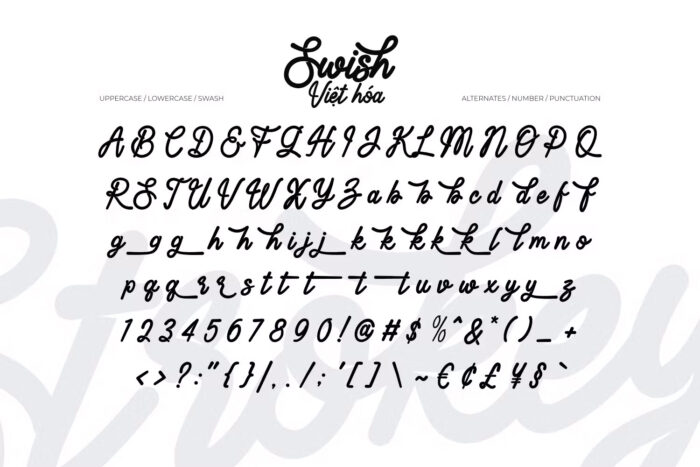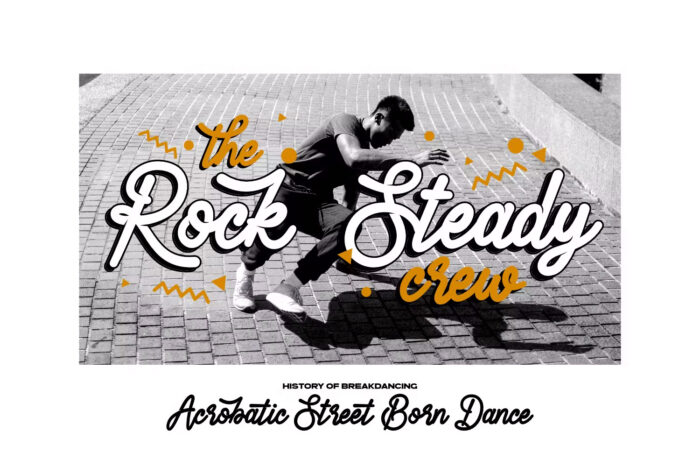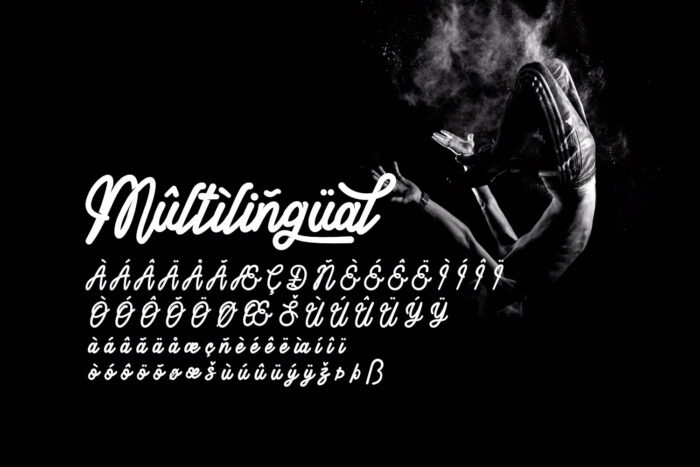
DVN Swish – Font chữ Việt hóa uyển chuyển và mềm mại
Swish Việt hóa là một font chữ monoline hiện đại, nổi bật với những đường nét uyển chuyển và mềm mại. Được thiết kế tỉ mỉ, Swish mang đến cảm giác nhẹ nhàng và thanh thoát, phù hợp cho các thiết kế đòi hỏi sự tinh tế và sang trọng. Những đường cong mượt mà của từng ký tự giúp tạo nên sự liên kết nhịp nhàng, dễ đọc và thu hút mắt người nhìn.
Font Swish Việt hóa không chỉ hỗ trợ đầy đủ các ký tự tiếng Việt mà còn cung cấp nhiều kiểu dáng thay thế và các yếu tố trang trí, giúp người dùng linh hoạt trong thiết kế. Đây là lựa chọn lý tưởng cho các dự án thiết kế logo, tiêu đề, bìa sách, thiệp mời, và các ấn phẩm quảng cáo. Với khả năng ứng dụng đa dạng và tính thẩm mỹ cao, Swish Việt hóa chắc chắn sẽ là điểm nhấn độc đáo trong bộ sưu tập font chữ của bạn.